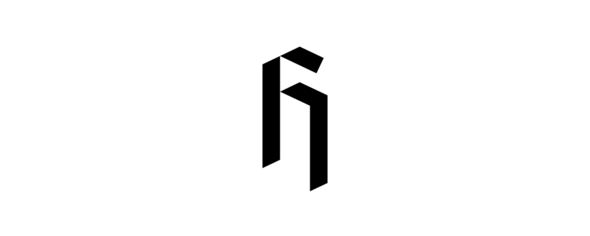
Schriftart herausfinden?
kann mir jemand sagen was das für eine Schriftart ist?
ich habe bereits versucht es mit tools wie "WhatTheFont" herauszufinden aber da es nur ein Buchstabe ist, findet kein Tool die Schriftart.
Dürfte Richtung Gotisch gehen wenn ich mich jetzt nicht ganz vertue.
Das scheint keine Schriftart zu sein, sondern ein Firmenlogo. (Allem Anschein nach von "Huber Digital Agentur"
Ggf. könntest du der Firma eine nette Email schreiben und fragen, ob es nicht doch von einer Schriftart inspiriert wurde und wenn ja, von welcher.